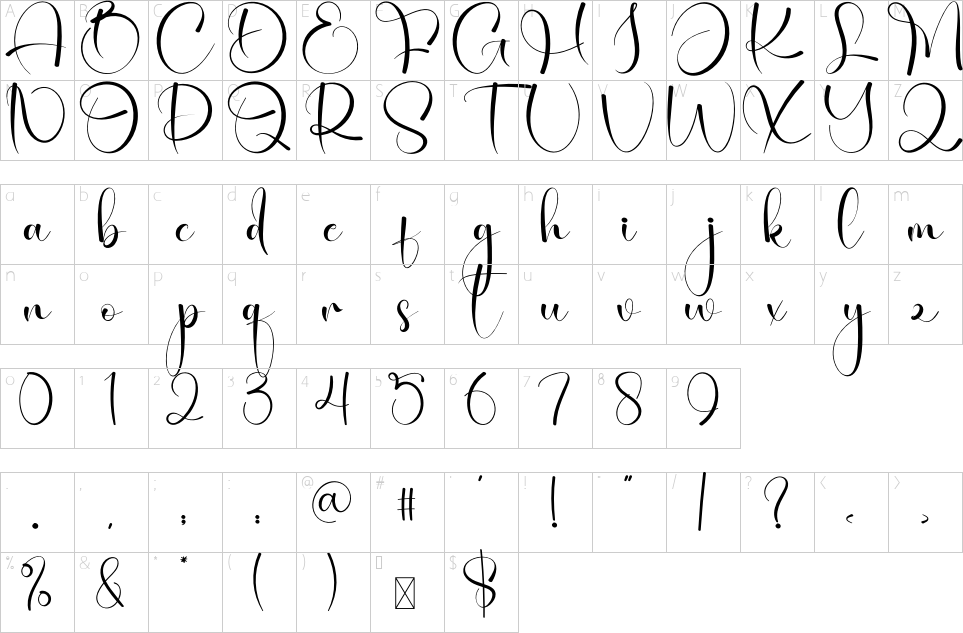
A fonte Paradise é uma opção gratuita para designers e criativos de todo o mundo. Ela foi projetada por scratchones e já foi baixada 675 vezes. Paradise oferece um design agradável e moderno, ideal para criação de designs de qualidade. Seja para cartões de aniversário, e-mails personalizados ou até mesmo como base para criação de logotipos, Paradise tem o poder de transformar seus projetos de uma maneira única. Sem compromissos de licenciamento, Paradise está disponível tanto para quem usa o Windows quanto para aqueles que preferem Mac. Sempre um passo à frente com a tecnologia, Paradise é uma escolha segura para aqueles que buscam qualidade e versatilidade em suas fontes de texto.